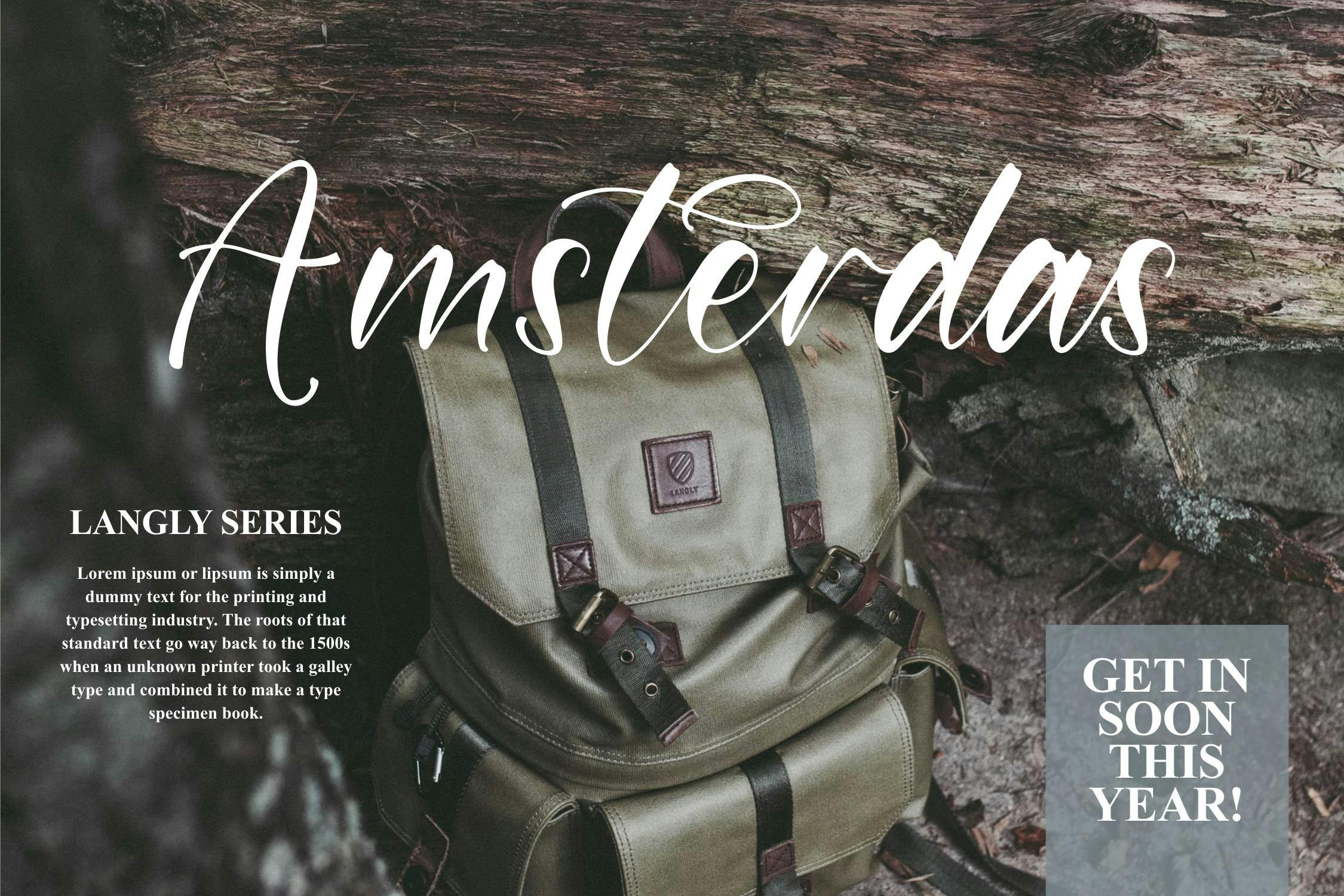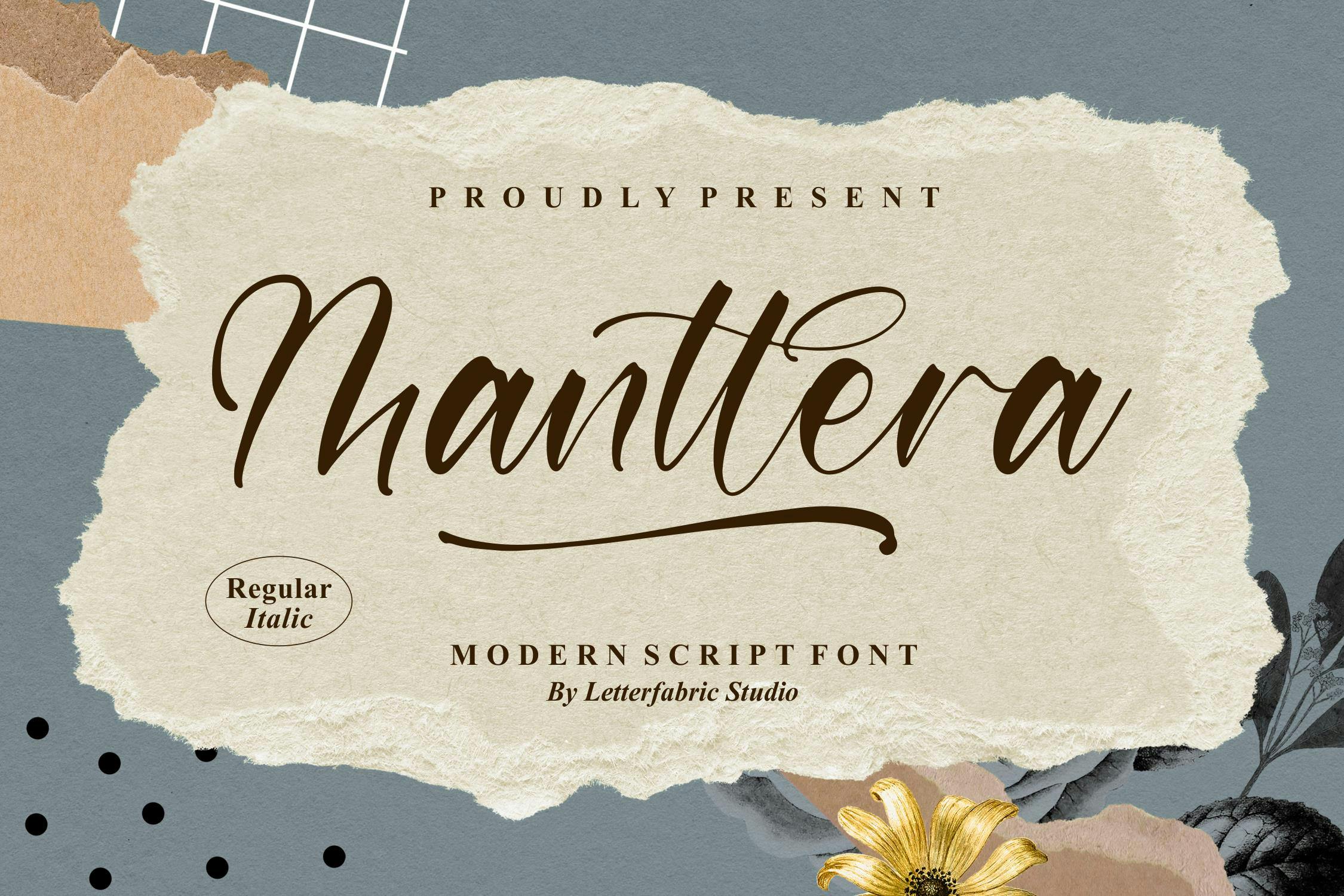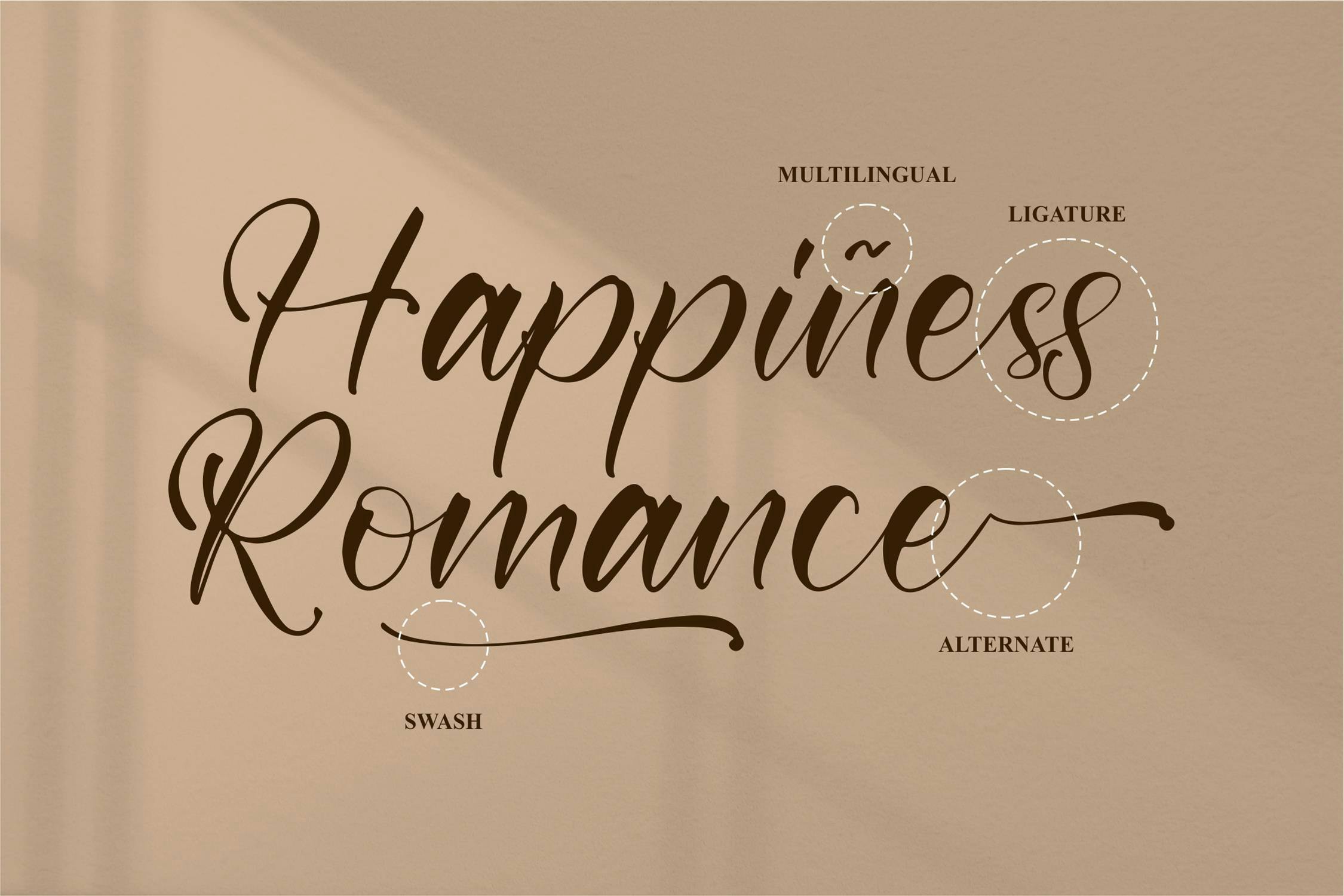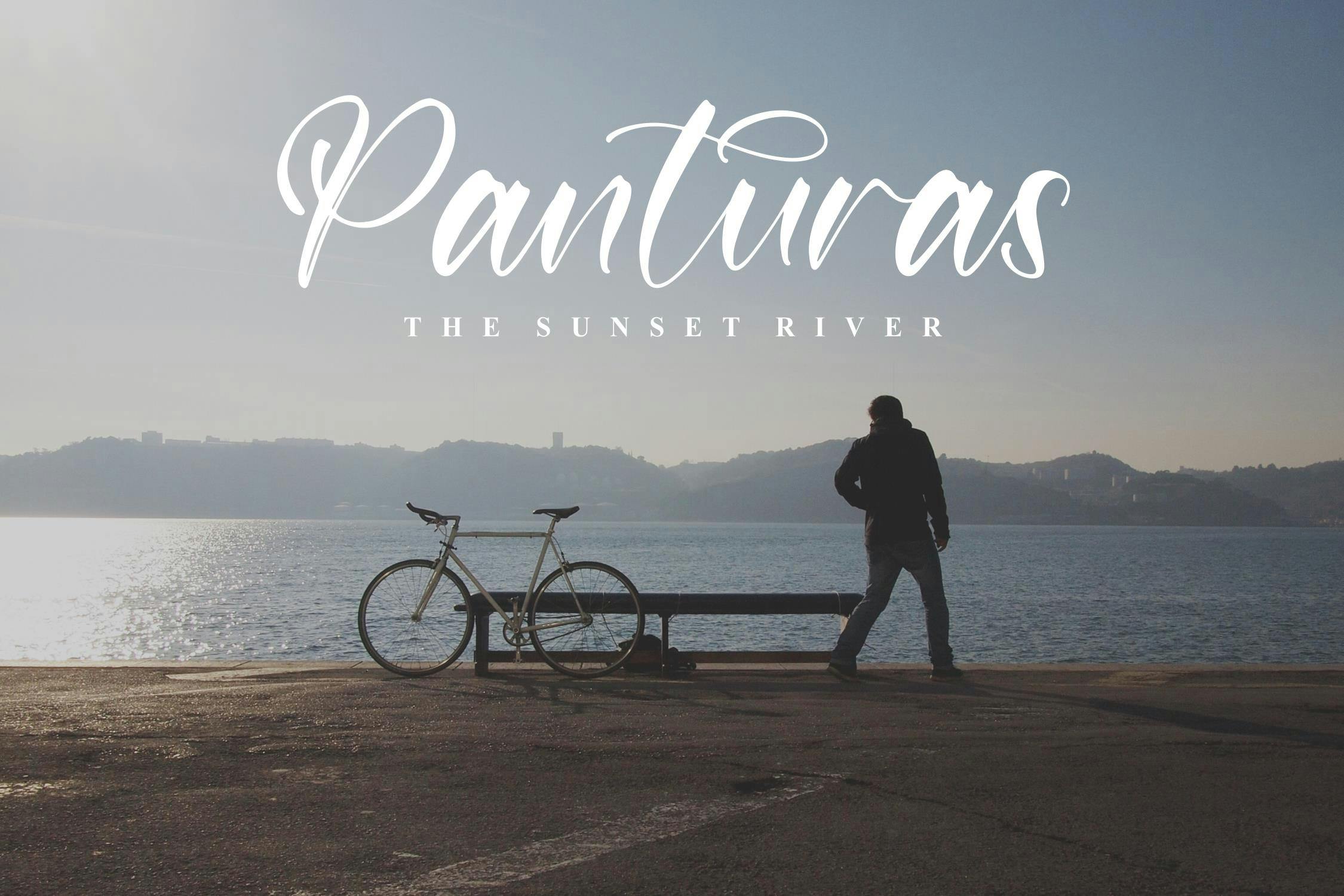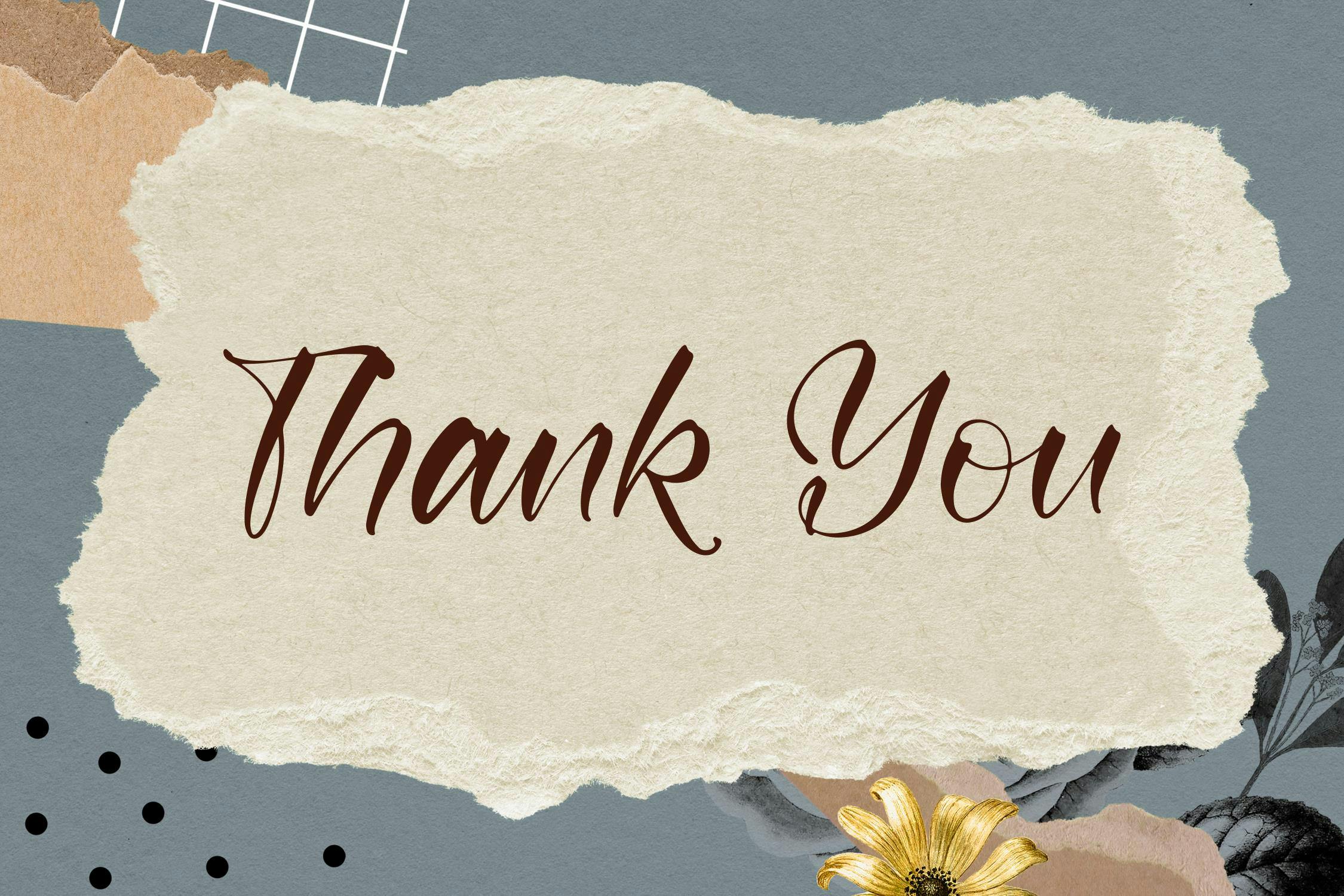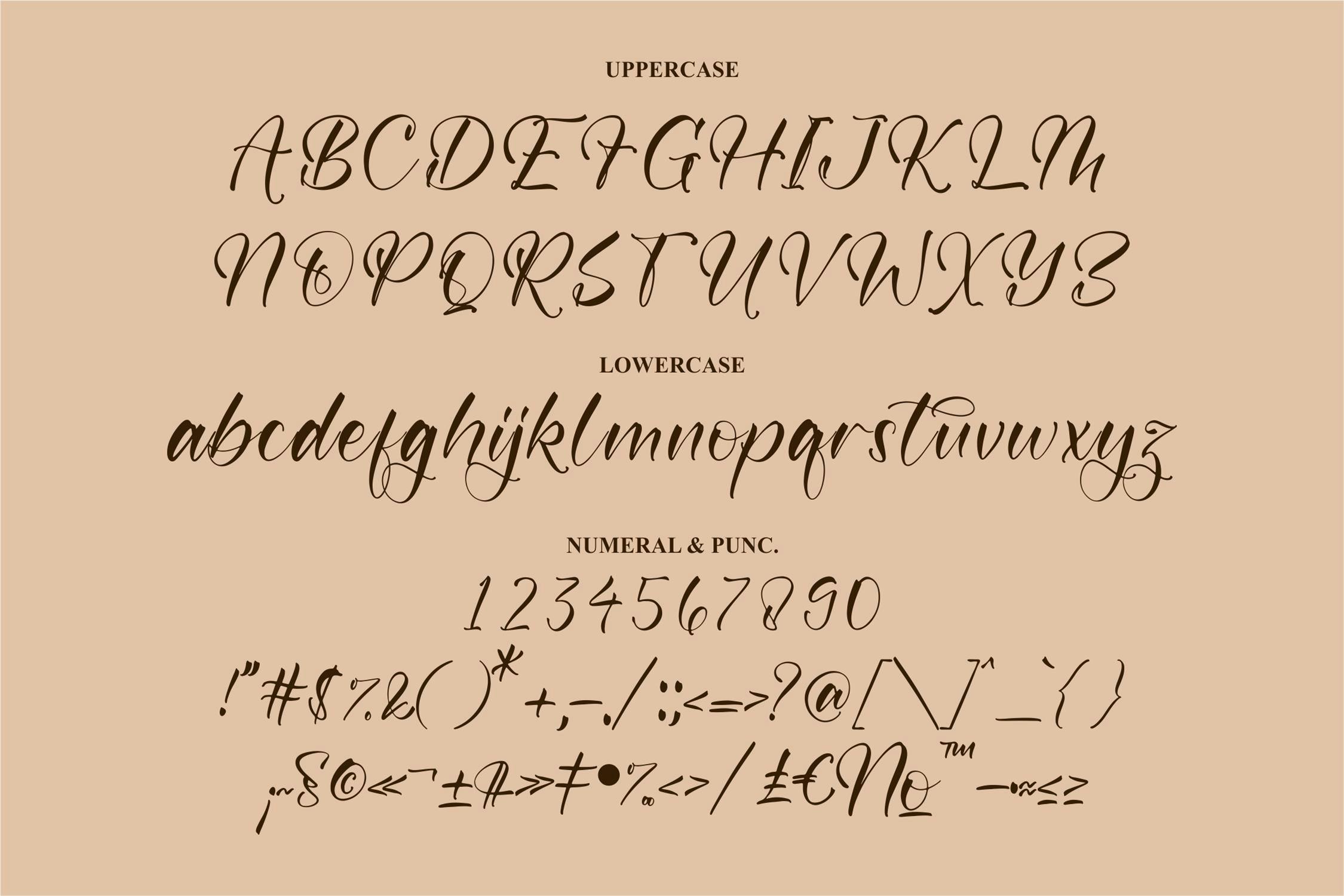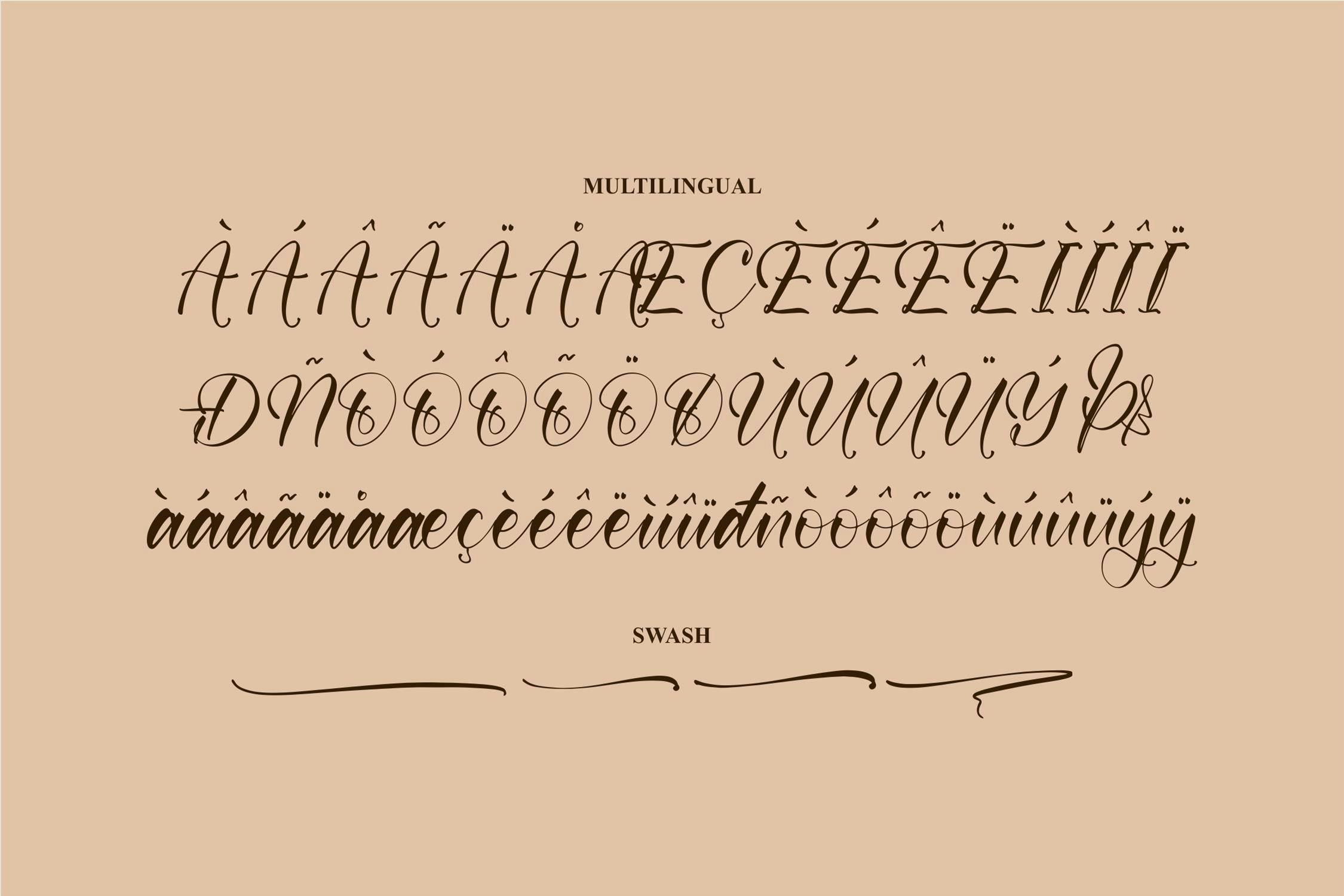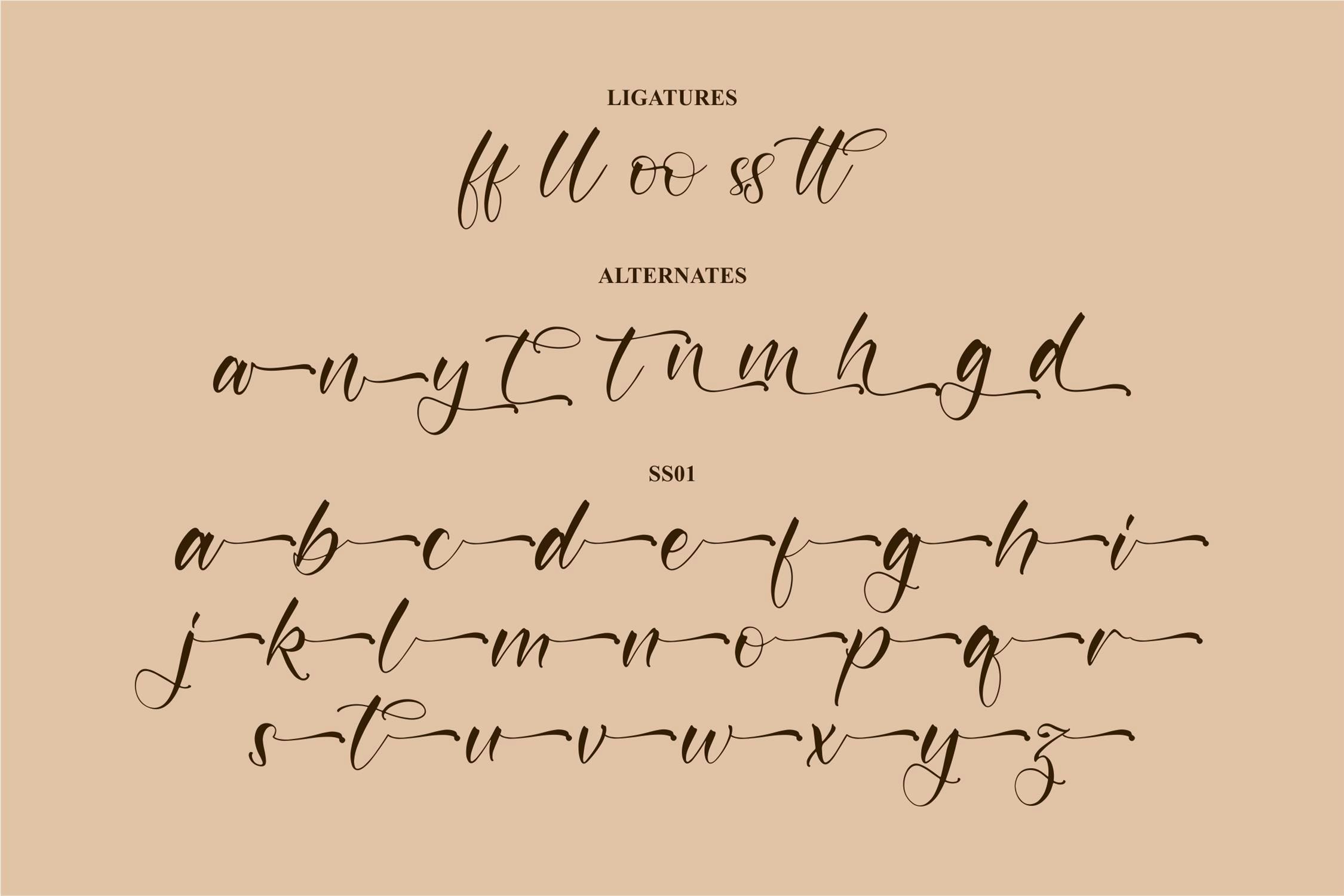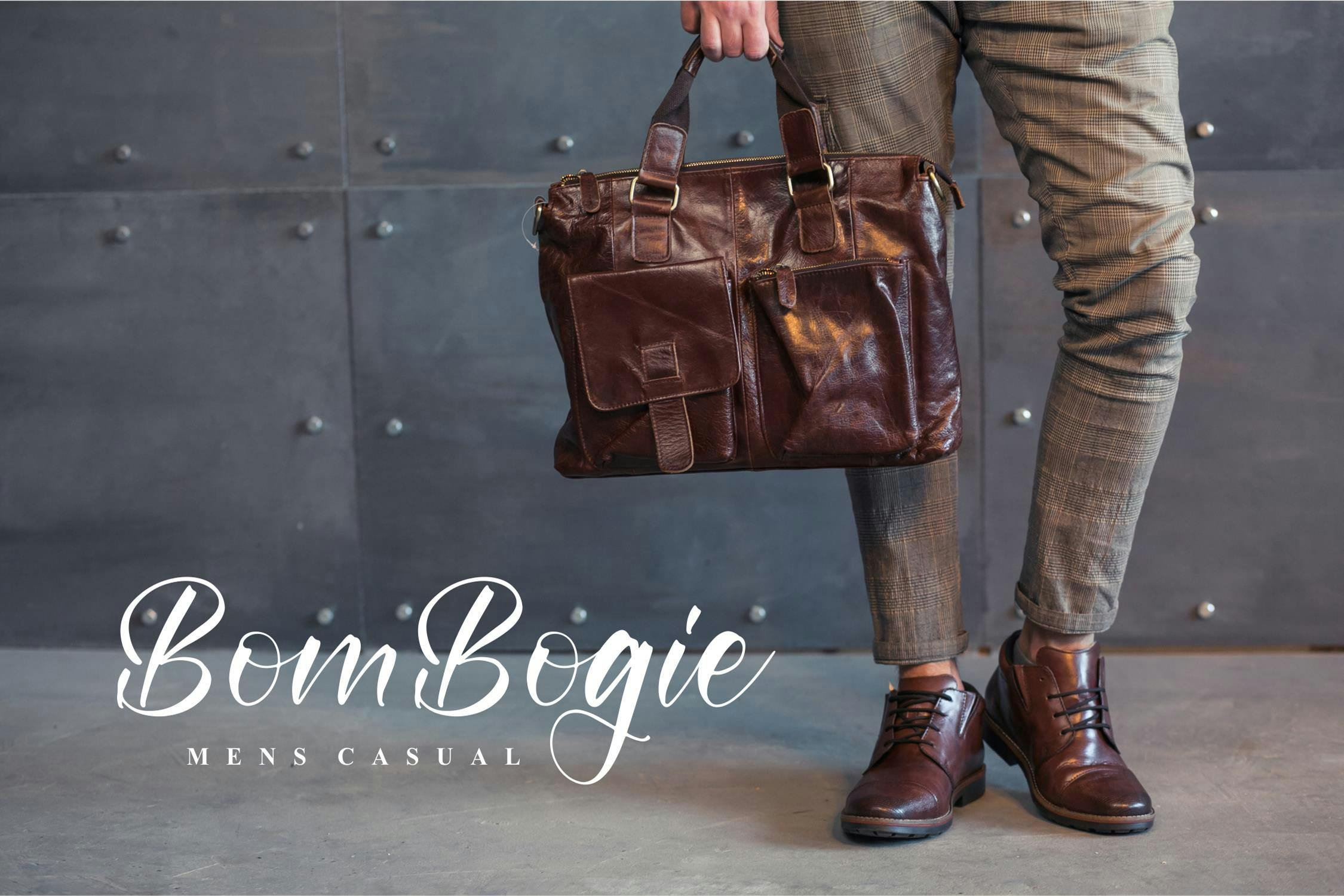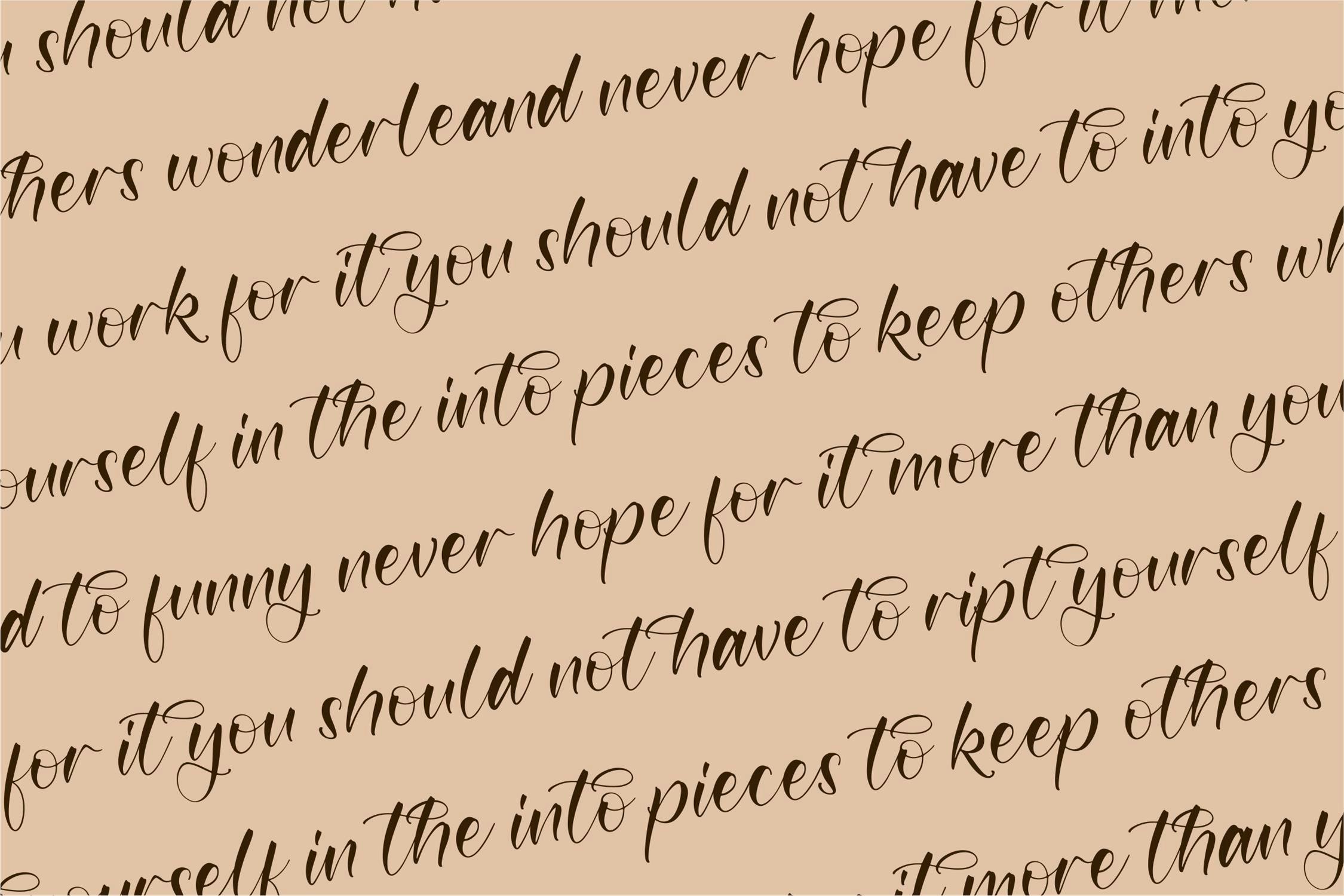
Manttera Modern Script Font
فونت Manttera Modern Script، انتخابی ایده‌آل برای طراحی‌های خلاقانه شما.
سلام خانم‌ها و آقایان، این یکی از فونت‌های ماست که مناسب برای تکمیل محصولات خلاقانه دیجیتال و چاپی شما می‌باشد.
این فونت برای پوسترها، پست‌های شبکه‌های اجتماعی، برندینگ، پروژه‌های شخصی و غیره ایده‌آل است.